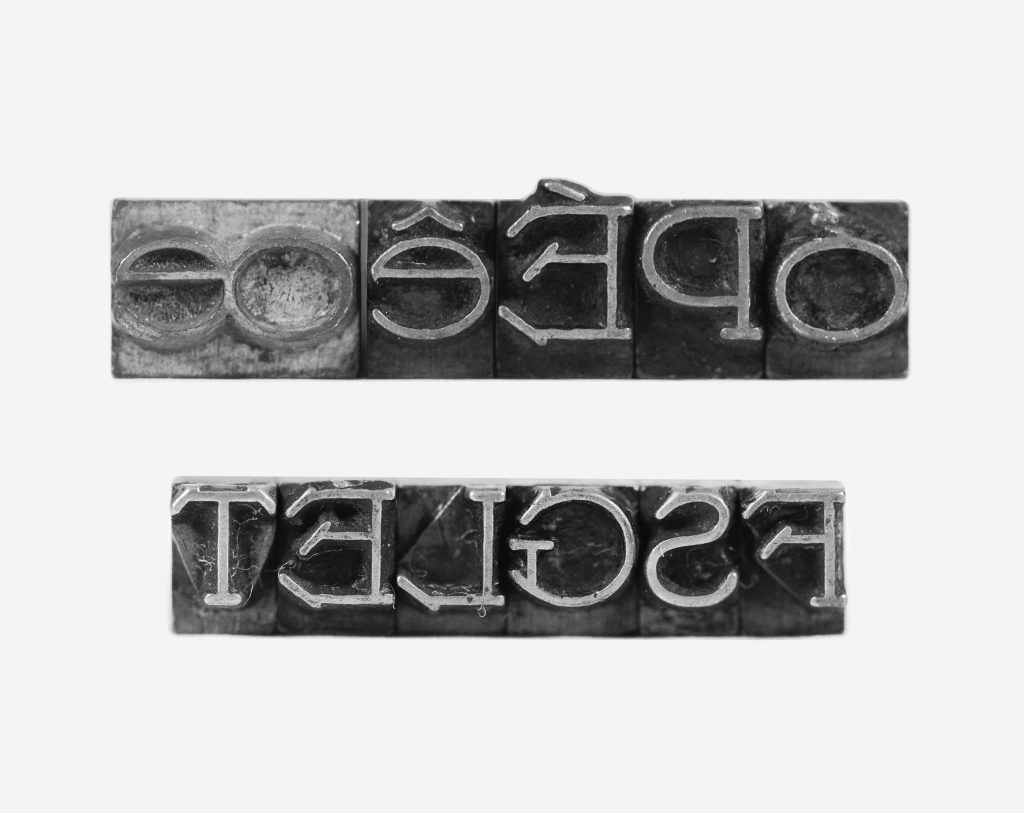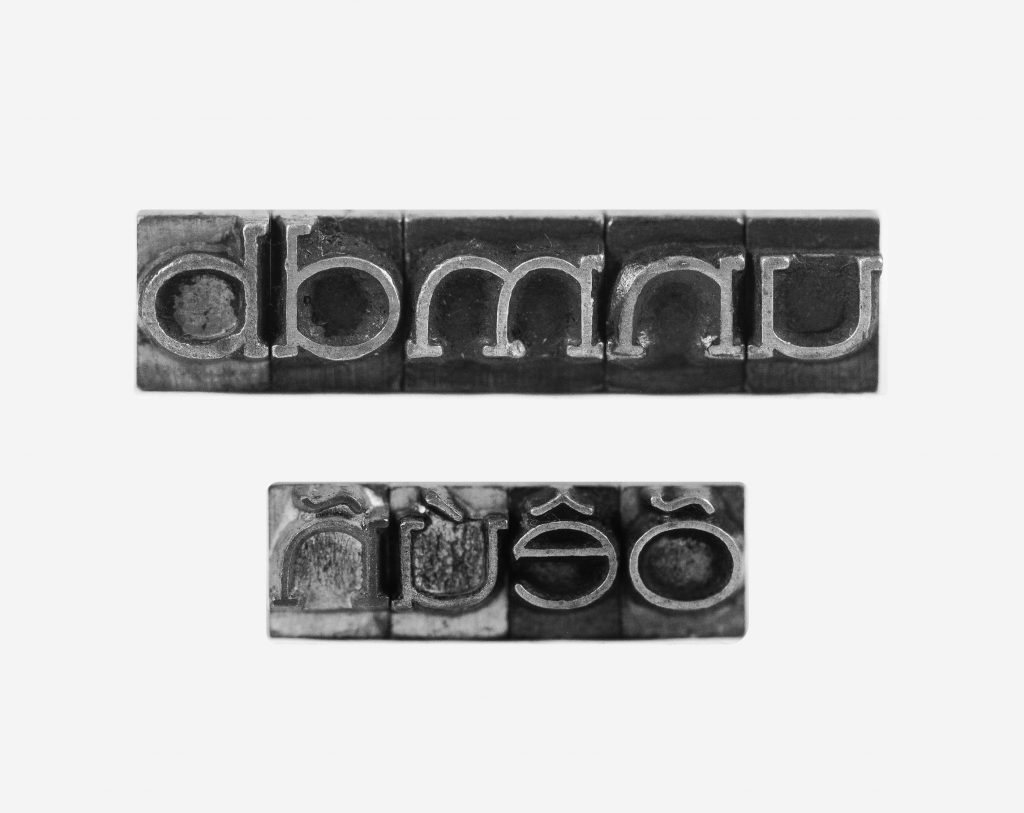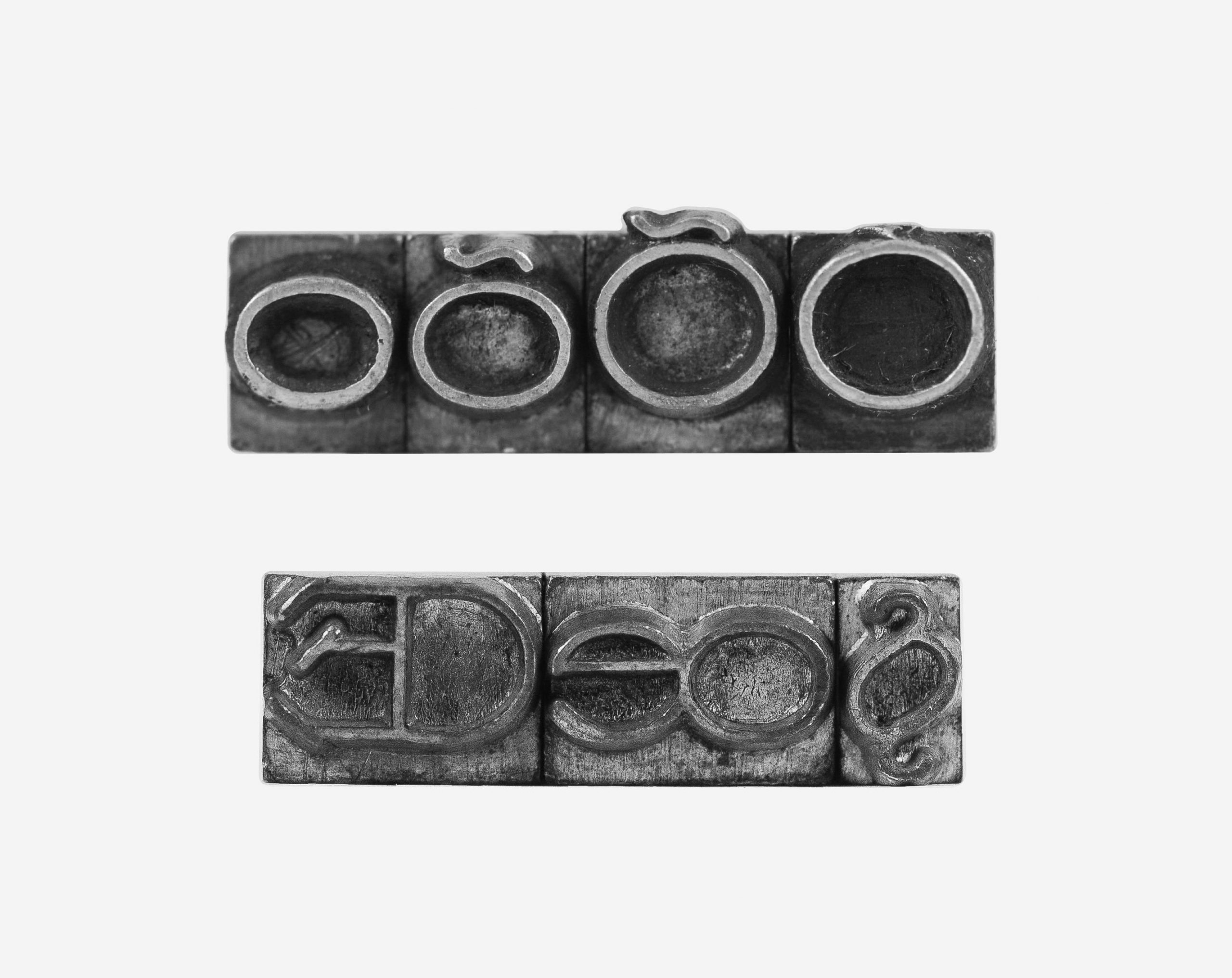
Identificação
[Bravour / Rolando 510-02] 16pt
Estilo
Serifada
Caracteres Chave
E, R, a, 2
Fundidora
[D. Stempel / Nebiolo]
Nebiolo, 1939; Escolas Profissionais Salesianas [s.d.]; Funtimod S.A. [entre 1958 e 1963] [capa laranja]
Marcas de uso recorrente; alguns tipos apresentam desgaste na face que pode comprometer a qualidade da impressão.
Maiúsculas | Minúsculas | Algumas maiúsculas acentuadas | Algumas minúsculas acentuadas | Numerais | Sinais | Ligaturas | Pontuações
Faltam algumas acentuadas, como: Ã, Á, Àà, Ââ, ê, É, Íí, Ìì, Óó, Ú, Ù
História do Estilo
Um desenho semelhante foi encontrado em um catálogo da Nebiolo (1939), em uma fonte nomeada como Roland 510-02. Segundo a plataforma Fonts in Use, este desenho foi baseado na tipografia Bravour, de Martin Jacoby-Boy, lançada inicialmente pela D. Stempel em três pesos, em 1912. Foi vendida pela Fondografica (como Velletri), Caslon (como Paladin, cinco estilos), Ardinghi (como Serie Moderna), Nebiolo (como Rolando), Fondografica (como Roma) e Funtimod (como Bravour). Sabe-se que uma versão ligh era fundida pelas Escolas Profissionais Salesianas (Nº 255, s.d., p.33) no corpo 24 pt.